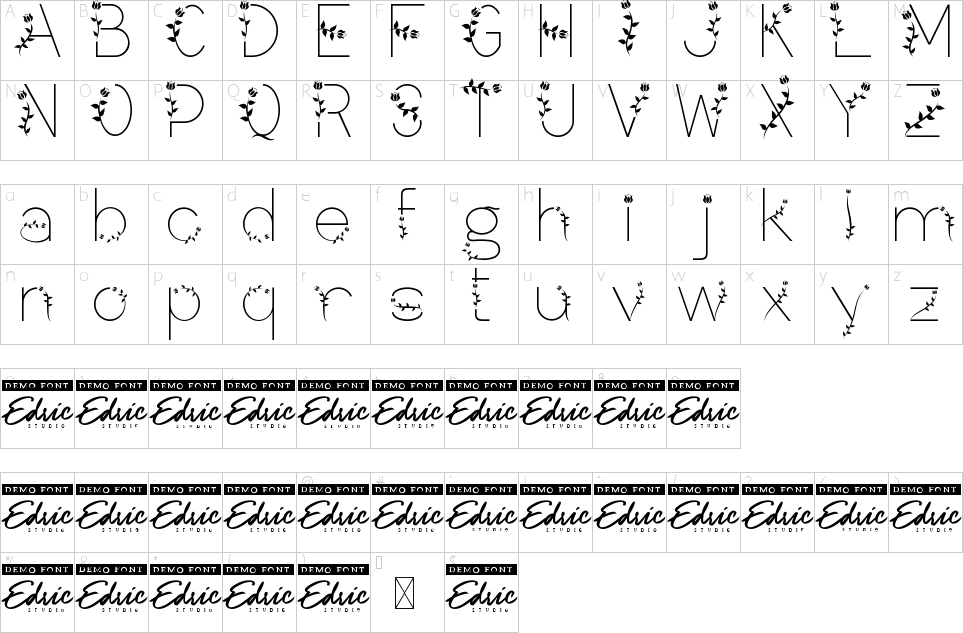
Aqui está uma descrição envolvente para a página de download da font ‘Flower Leaf Font’, com 2 parágrafos curtos: Aproveite esse lindo conjunto de fontes florais que se assemelham às folhas e flores. A EdricStudio criou esta font exclusiva, perfeita para aqueles que buscam uma mistura única entre o elegante e o natural. As letras têm um toque delicado e feminino, sem perder a simplicidade de qualquer letra floral convencional. Adornar seus documentos ou projetos com essa font não apenas tornará seu trabalho mais atraente, mas também trará uma sensação de frescura e vitalidade ao design. Estará disponível tanto para uso no Windows quanto em Mac, garantindo sua conveniência ao utilizar na versão que preferir. Com um total de 4.782 downloads, é evidente o apreço por essa font elegante e sofisticada. Seja você designer gráfico, blogger ou ilustrador, a ‘Flower Leaf Font’ oferece a chance de criar algo único e incrivelmente belo.